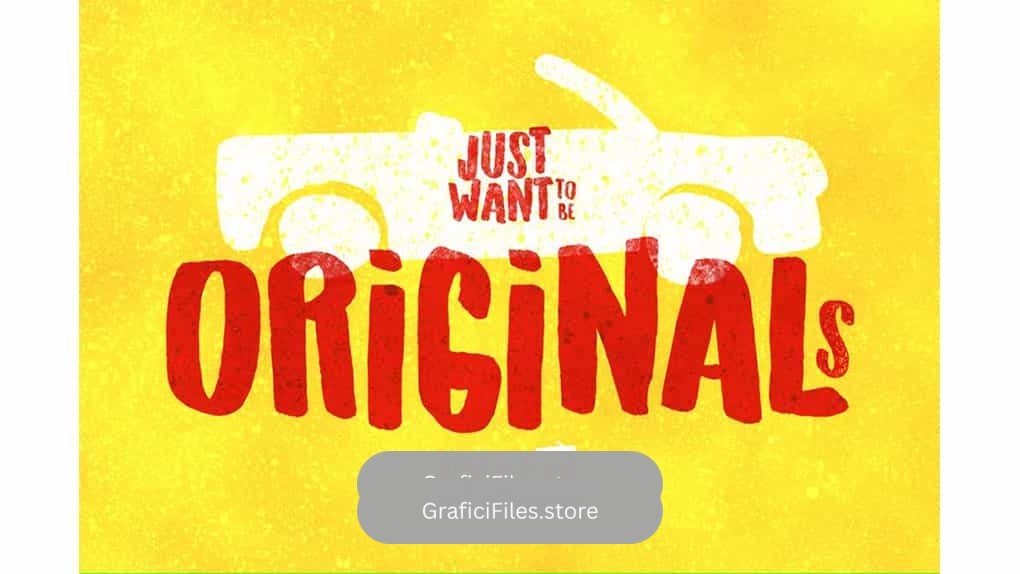
فونت انگلیسی Originals Typeface : این مجموعه شامل یک فونت دست نویس است که برای تابلو ها، تی شرت ها و کارت مناسب میباشد.
• عنوان مجموعه: Originals Typeface
• سبک: N/A
• فضا بین حروف: معمولی
• اندازه بهینه: تمامی سایز ها